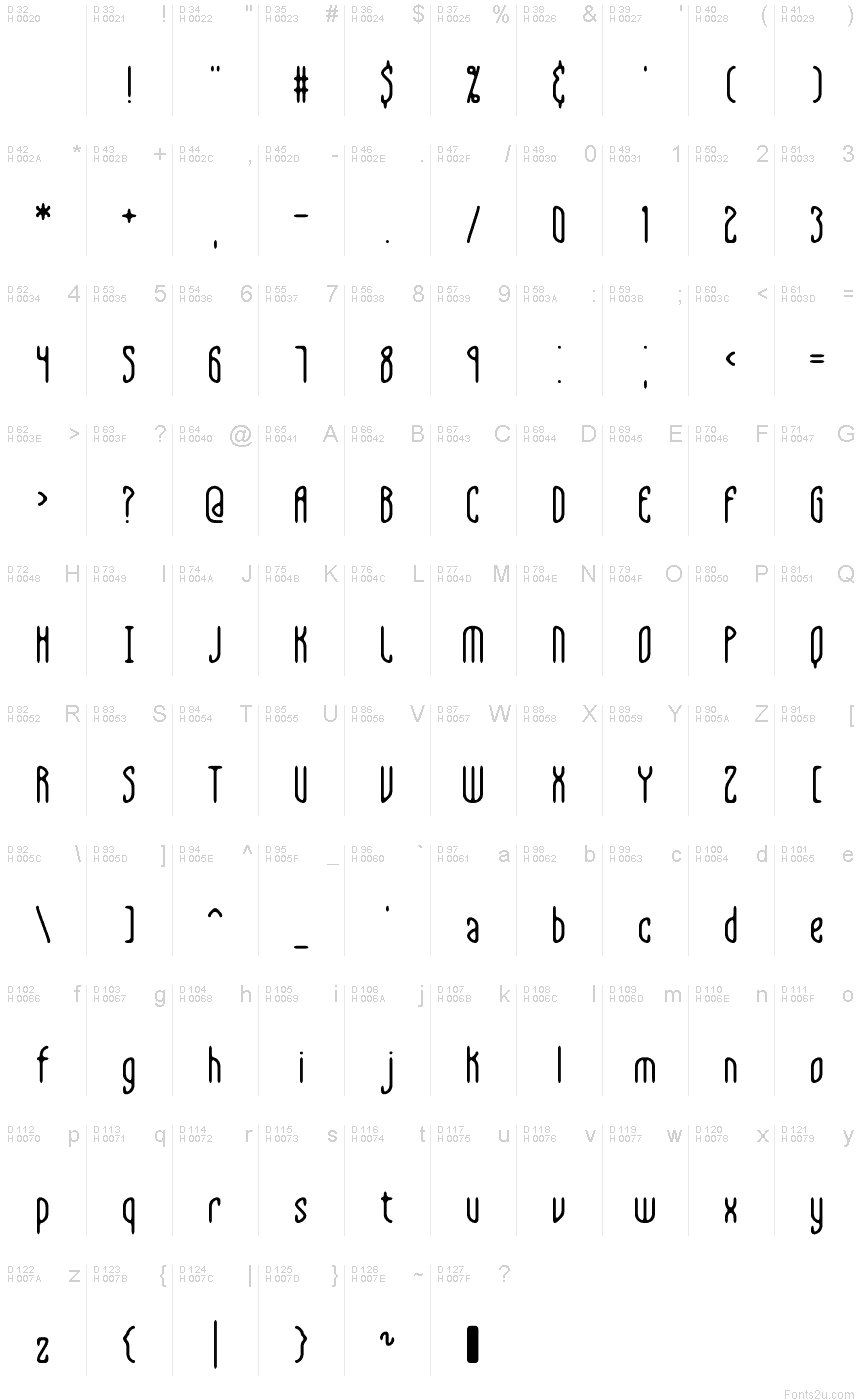
Supra Genius Curves BRK
Supra Genius Curves BRK di ÆNIGMA Fonts è un carattere display gratuito, sinuoso e con un tocco ludico che ricorda l'Art Nouveau. Le lettere si allungano in tratti lunghi e sinuosi con ganci arrotondati, conferendo al carattere un ritmo fluido e disegnato a mano, più ornamentale che geometrico.
È perfetto per poster, packaging di boutique, copertine musicali, menu di caffè e brevi lavori di logo design dove un font gratuito può creare l'atmosfera da solo. Usalo per titoli, schede di presentazione o iniziali in stile monogramma quando vuoi lettere che si arricciano e ondeggiano invece di stare ferme.